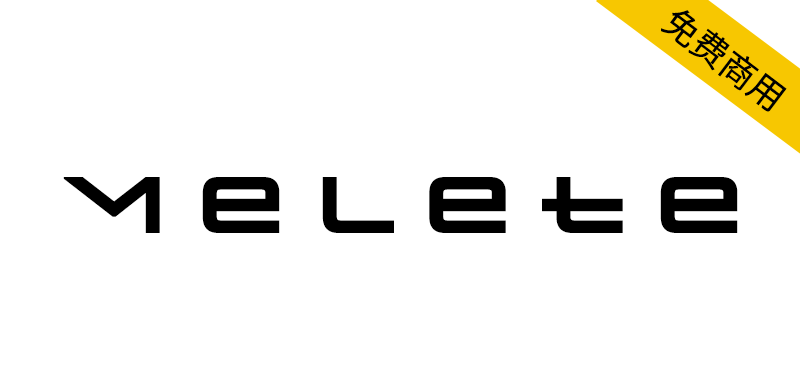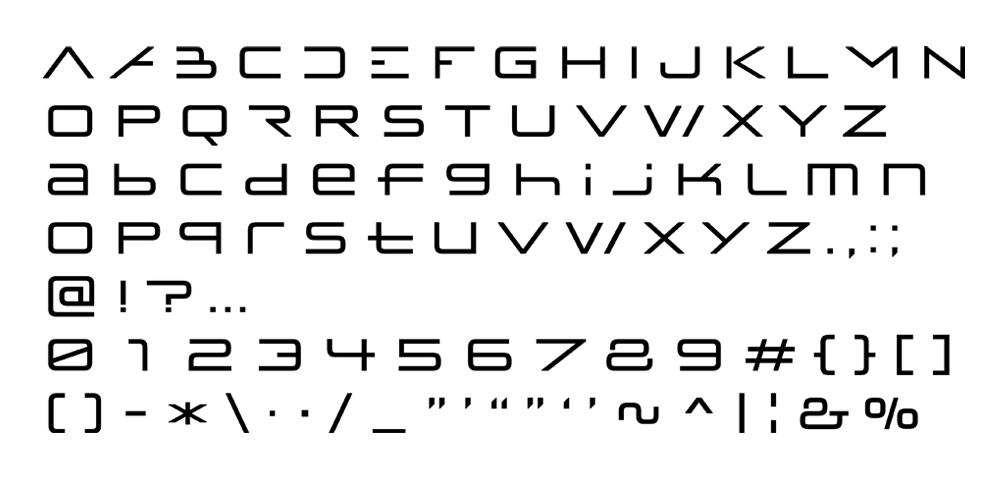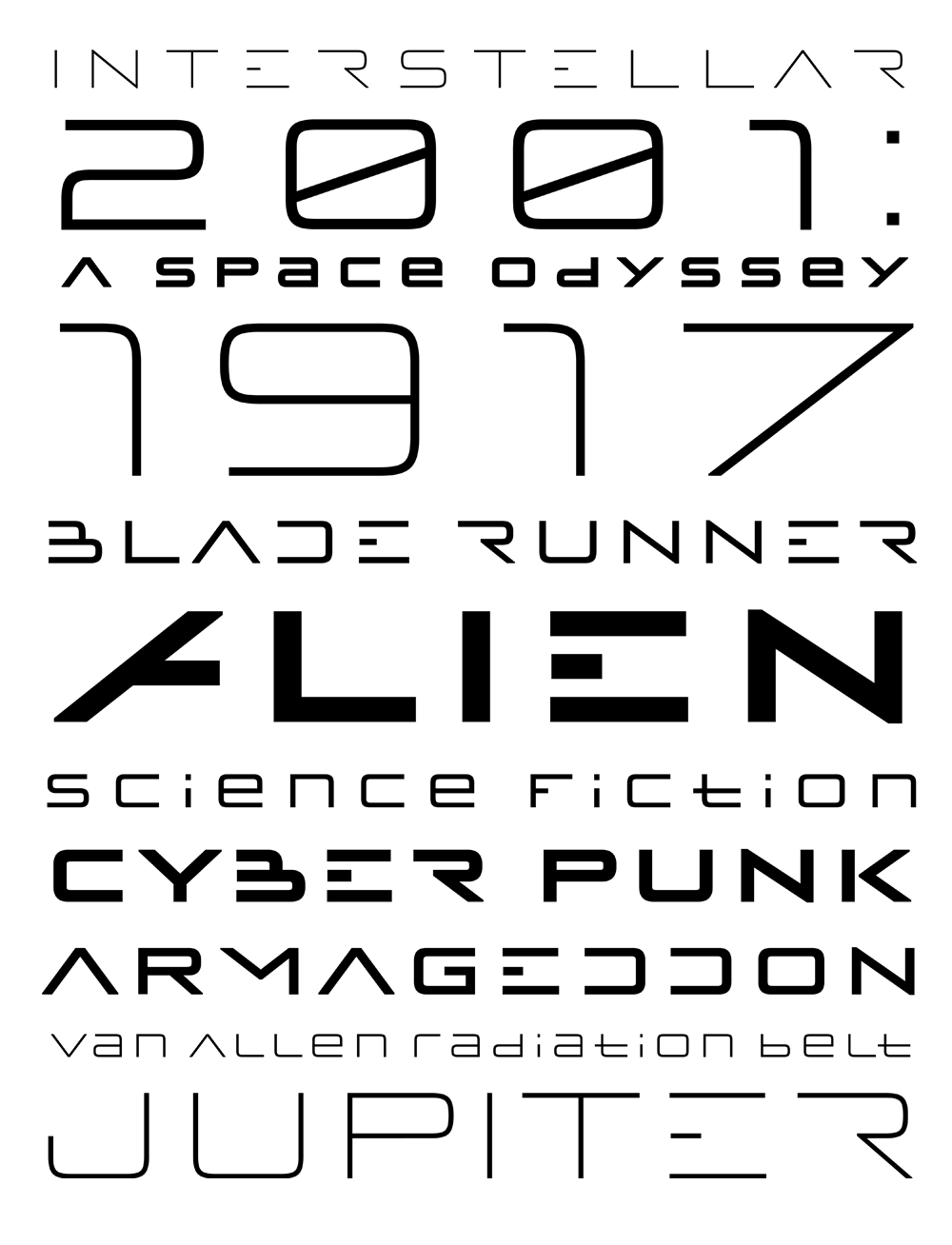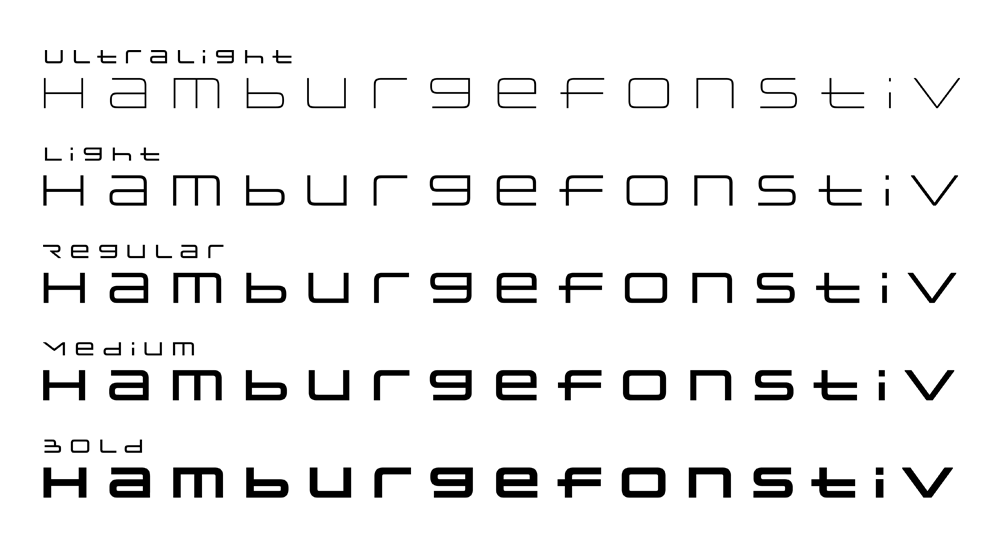
Melete 是一种无衬线字体,旨在营造科幻电影标题的感觉。
在牺牲一些可读性的同时,我们创造了慷慨的留白来营造一种未来主义的氛围。
我们的目标是更加前卫的设计,参考了科幻电影中经常使用的Eurostile Extended和Bank Gothic 。
目前,这是一个测试版本,仅包含基本的大小写字母、数字和符号。
MeleteはSF映画のタイトルのような雰囲気を目指したサンセリフです。
可読性を一部犠牲にしつつ、ゆったりとした余白を用意し近未来的な雰囲気になるよう仕上げました。
よくSF映画で使われているEurostile ExtendedやBank Gothicを参考に、より尖ったデザインを目指しています。
現在のところ、基本的な大文字・小文字のアルファベット・数字・記号類のみ収録しているベータ版となります。